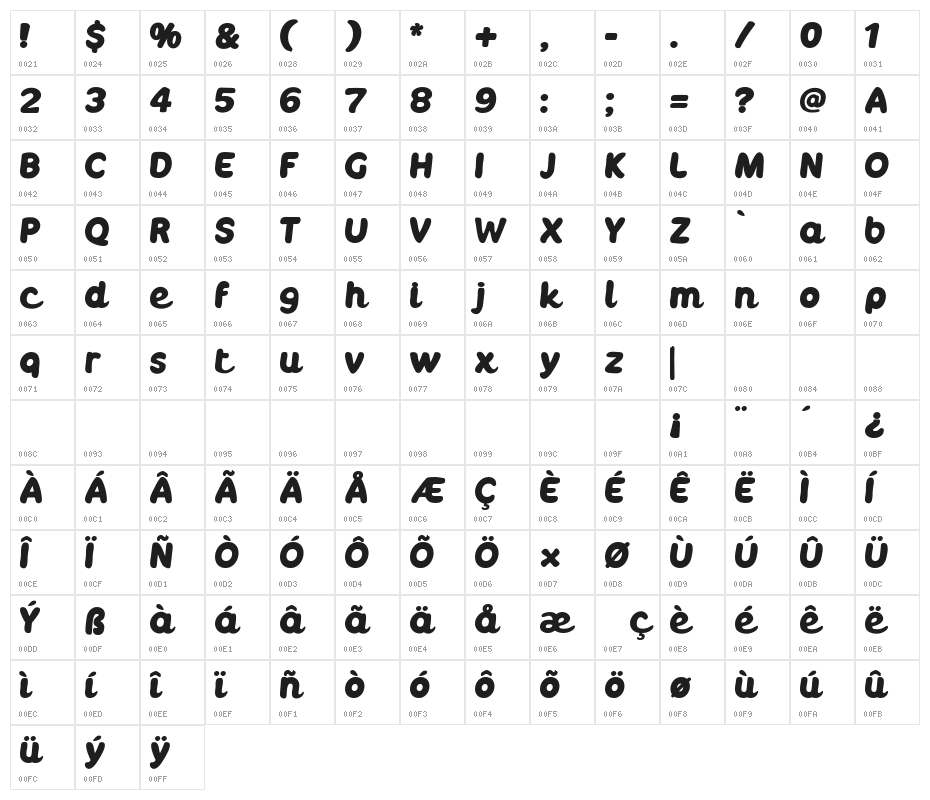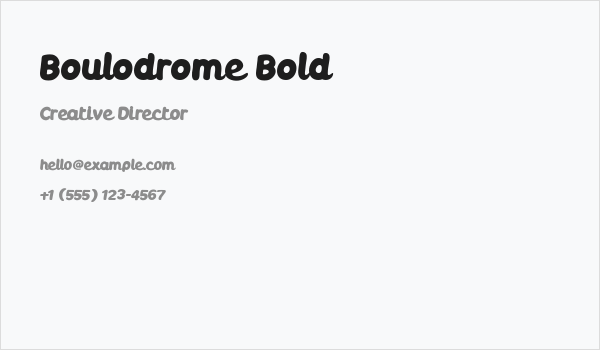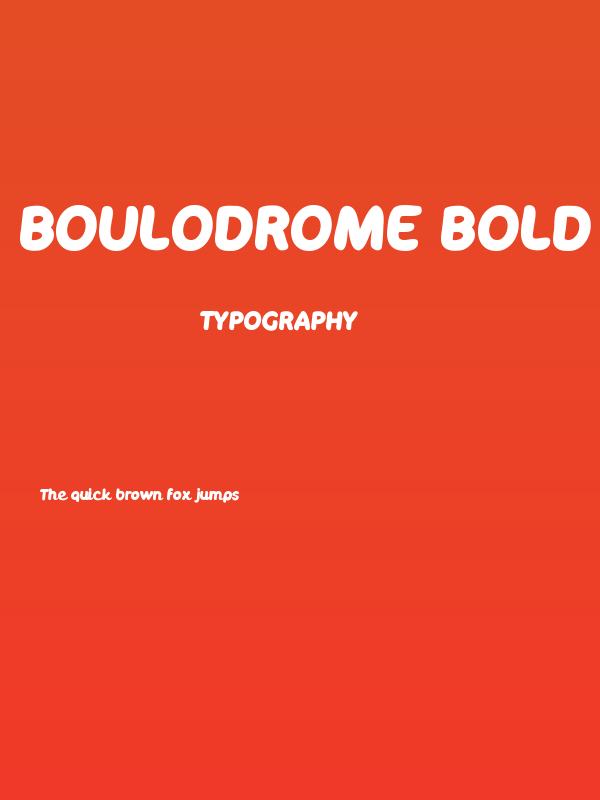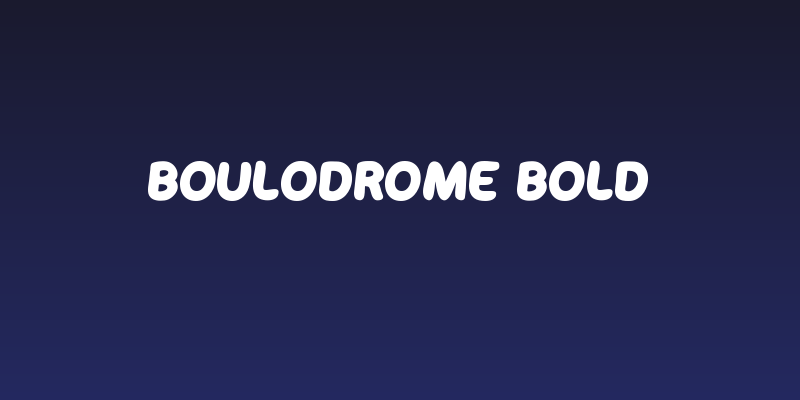
Boulodrome Bold Font
| Estilo general | Playful |
| Caso de uso | Headlines, Logos, Informal Text |
| Proyectos propuestos | Ideal for children's books, playful branding, casual invitations, and friendly advertising campaigns. |